「ファンシー」にぴったりの日本語フリーフォント
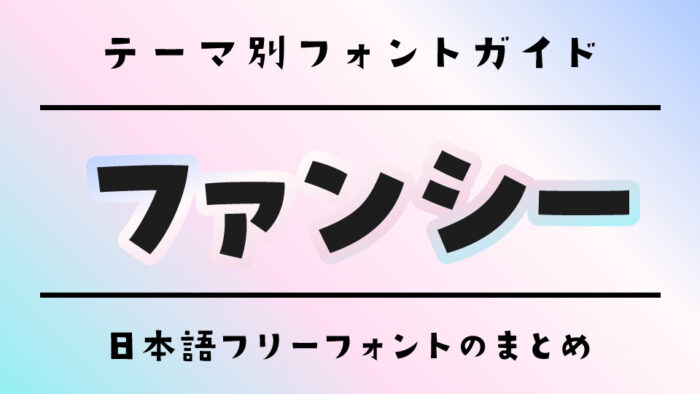
今回は、ゆるふわ♡な雰囲気たっぷりの「ファンシー」にぴったりな日本語フリーフォントをご紹介します。
リボンやレース、パステルカラー、キラキラしたモチーフなど、そんな可愛くてふわふわとした“ファンシー”の世界を彩るには、フォントにもときめきが必要です。
まるみのある文字や、少女っぽさを感じる筆跡、ちょっと気の抜けたゆるさを持ったデザインは、見ているだけで胸がキュンとしますよね。
今回は、ファンシー雑貨風のロゴや、SNSのネームロゴ、動画テロップ、手紙風デザインなどファンシーな表現をしたい場面にもぴったりな日本語フリーフォントをピックアップしました。
ファンシー感あふれる日本語フリーフォント
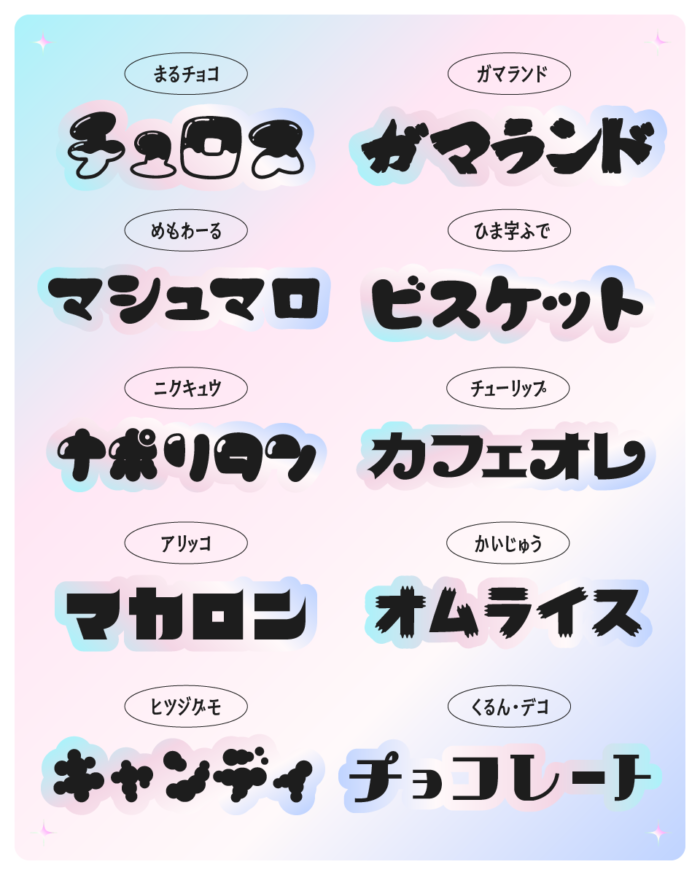
子パンダフォント
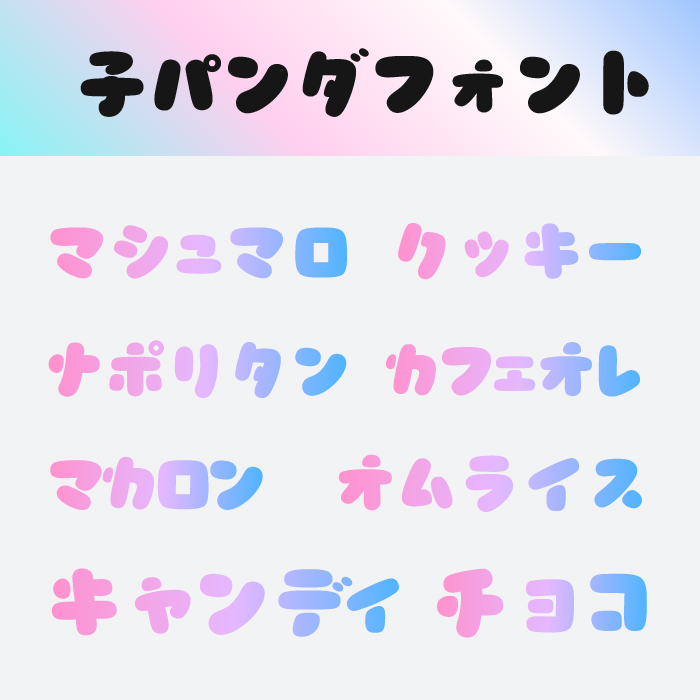
子パンダフォントは、丸くふっくらした形にほんのり甘さが漂う、愛嬌たっぷりのフォントです。パステルカラーとの相性も抜群で、マシュマロやチョコなどの言葉にやさしく溶け込みます。ゆめかわ・スイーツ系のデザインにぴったりなフォントです。
ひま字ふでフォント
ひま字ふでフォントは、手書きのような丸みと柔らかさが特徴で、優しい空気をまとったフォントです。角のない線が文字に親近感を与え、ポップながらもナチュラルな雰囲気が感じられます。女の子らしいデザインにぴったりなフォントです。
ふわふでフォント
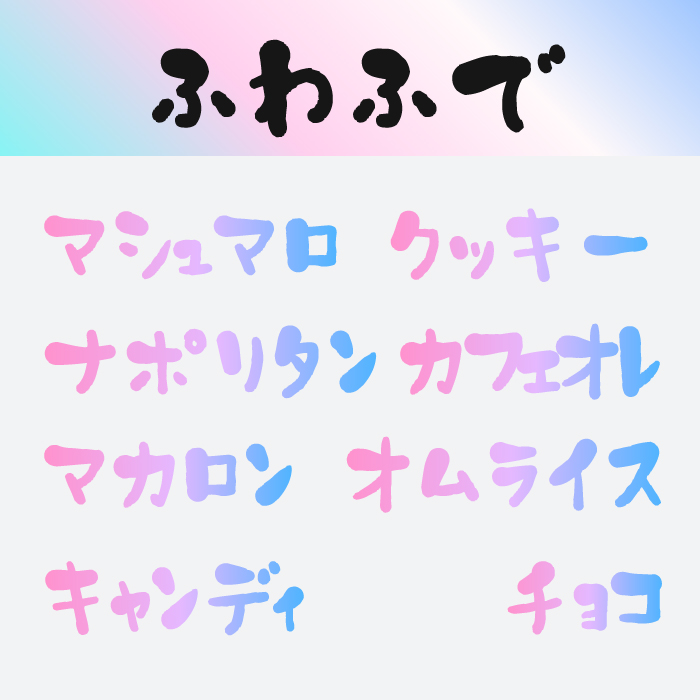
ふわふでフォントは、線の太さに揺らぎがあり、まるで雲のような柔らかさが広がるファンシー×筆系フォントです。全体に丸くふんわりとしたシルエットで、ほっこり感とゆるさが同居しています。ゆめかわ・癒し系のビジュアルにぴったりなフォントです。
ニクキュウ
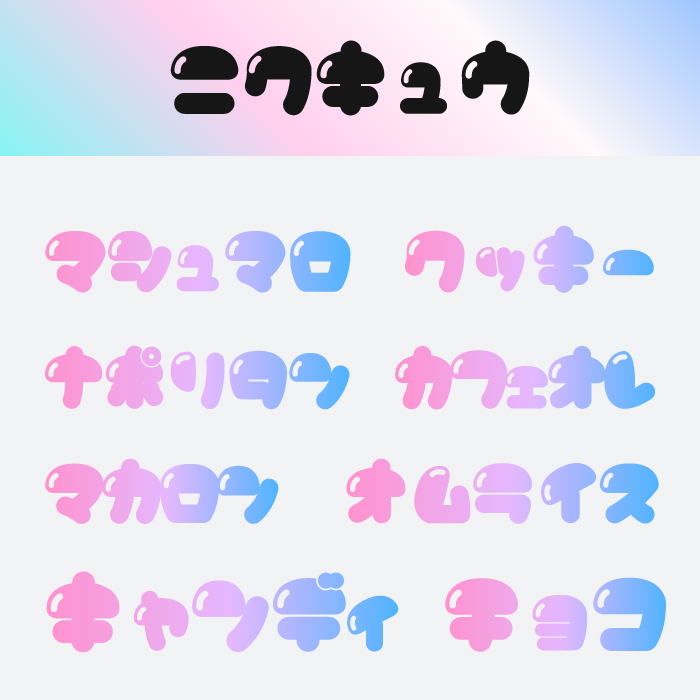
ニクキュウフォントは、文字にぷっくりとした光沢感があり、まるでキャンディやマカロンのような見た目が楽しいフォントです。丸いフォルムとツヤ感が、キュートさをさらに引き立てます。ファンシーで元気な表現にぴったりなフォントです。
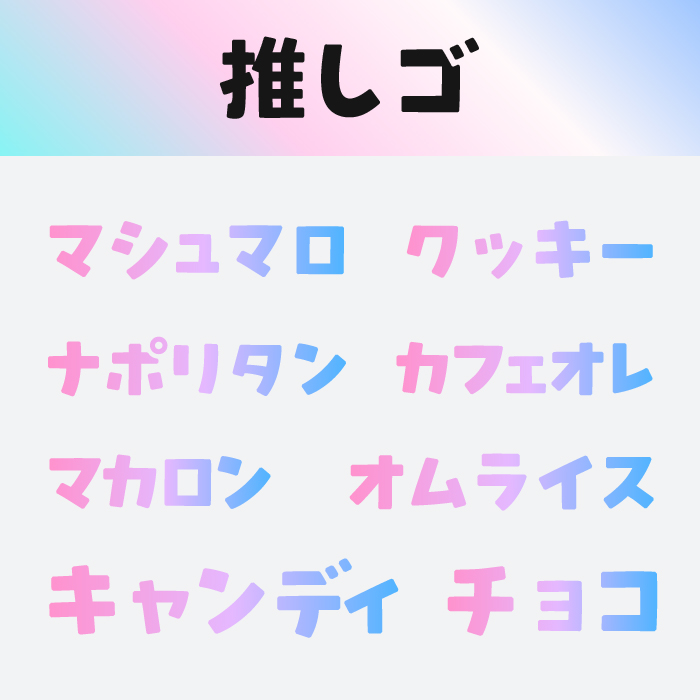
推しゴフォントは、シンプルな構成ながらも、丸みとすっきり感を兼ね備えた使いやすいフォントです。クセが少なく、ほどよい甘さで主張しすぎないのが魅力です。ガーリーなロゴやグッズづくりにぴったりなフォントです。
ぽーらリリィ
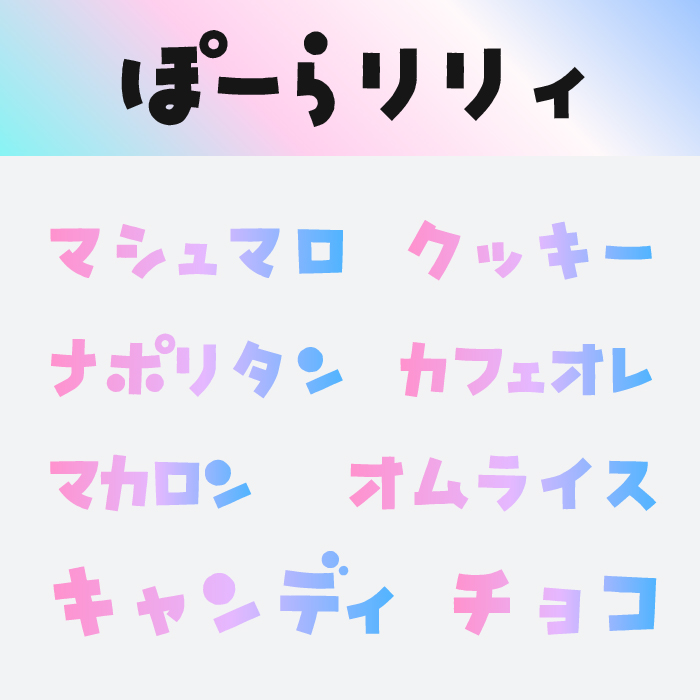
ぽーらリリィフォントは、文字の一部に小さな装飾が入り、楽しげで個性的なリズムを感じさせるフォントです。ひらがなの傾きや丸みが特徴的で、遊び心を演出したいときに重宝します。ポップでファンシーな世界観にぴったりなフォントです。
フローラ
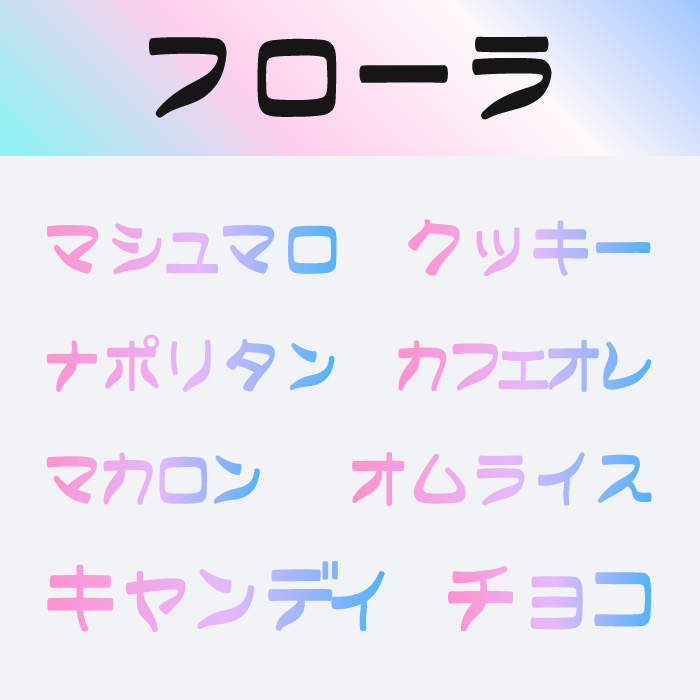
フローラフォントは、なめらかでしなやかな曲線が美しいファンシーフォントです。全体のフォルムに丸みとスリムさがあり、洗練された印象と可愛さを両立。ガーリー雑貨やロゴ、タイトルデザインに活躍するおしゃれなフォントです。
うたミンフォント
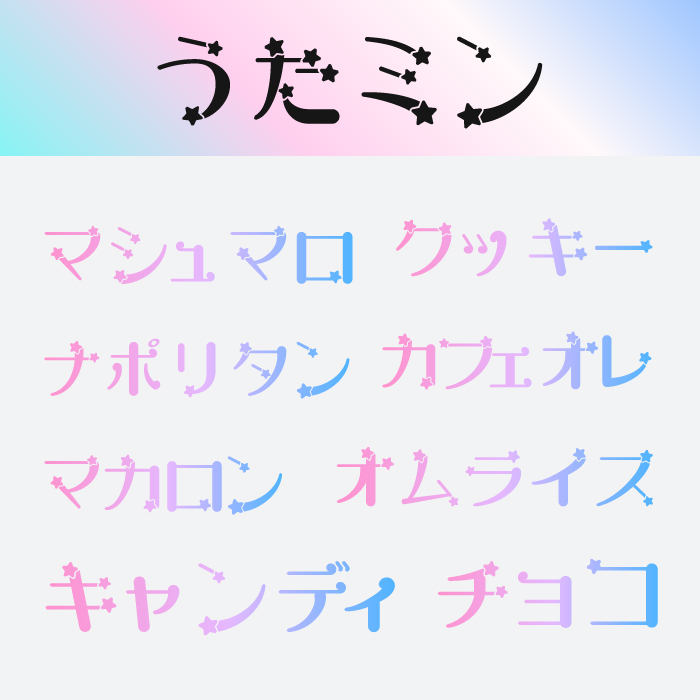
うたミンフォントは、文字の端々にキラキラの星があしらわれた、夢と魔法の世界を感じさせるフォントです。装飾的ながらも読みやすく、ロゴや見出しで特別感を演出できます。キラキラ系やファンシー表現にぴったりなフォントです。
くるん・デコ
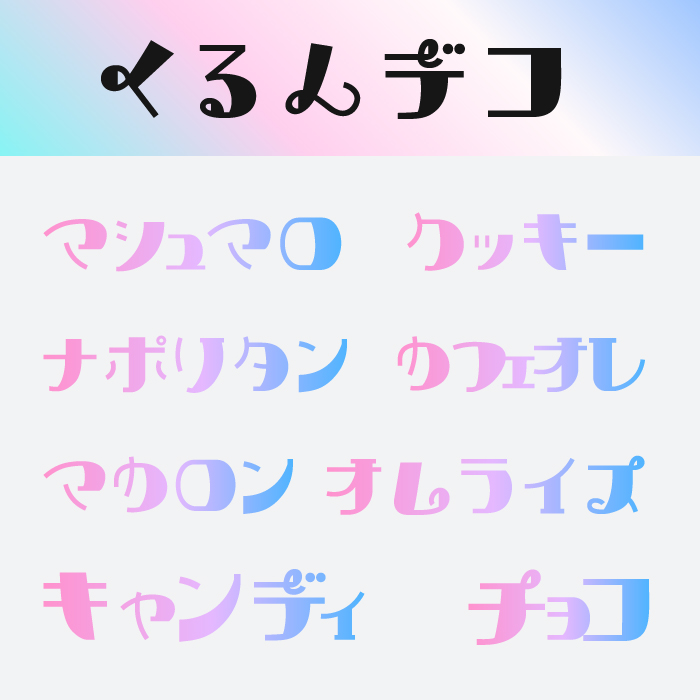
くるん・デコフォントは、文字の一部がくるんとデコレーションされた、装飾性の高いガーリーフォントです。やわらかな色彩と合わさることで、さらに可愛らしさが引き立ちます。ネームロゴやガーリー雑貨にぴったりなフォントです。
かいじゅうフォント
かいじゅうフォントは、線先がギザギザとした筆タッチのような豪快なシルエットが特徴で、元気なポップ感とかわいさを併せ持つ個性派フォントです。ファンシーなパステル配色とも意外とマッチし、インパクトのあるタイトルやキービジュアルにぴったりです。
ヒツジグモフォント
ヒツジグモフォントは、泡のように丸いパーツが集まって構成された、柔らかでぷくぷくとしたフォントです。動きのあるかたちとユーモアのあるバランスで、マシュマロやグミ、スイーツをテーマにしたファンシーな世界観にぴったりです。
チューリップ
チューリップフォントは、花びらのようなやさしいカーブと愛らしい装飾が施されたガーリーフォントです。グラデーションやパステルカラーとの相性もよく、タイトルロゴや装飾文字として使うとファンシーな雰囲気が一気に高まります。
めもわーる
めもわーるフォントは、手描き風のあたたかみと丸みのある書体が特徴で、柔らかく落ち着いた雰囲気を演出できます。お菓子や雑貨のデザイン、ゆるふわなメッセージ用途にも向いていて、親しみを感じさせるファンシーな印象のフォントです。
パクチー
パクチーフォントは、形がぷにっと膨らんだ独特の文字で、存在感と個性を兼ね備えたユニークなファンシーフォントです。文字の中に動きがあり、見ていて楽しくなる形状で、グッズやPOPデザインにもぴったりな印象です。
大大大大だぁい好き
大大大大だぁい好きフォントは、手書きの勢いとゆるさをそのまま活かした、賑やかで元気いっぱいの可愛いデザインフォントです。